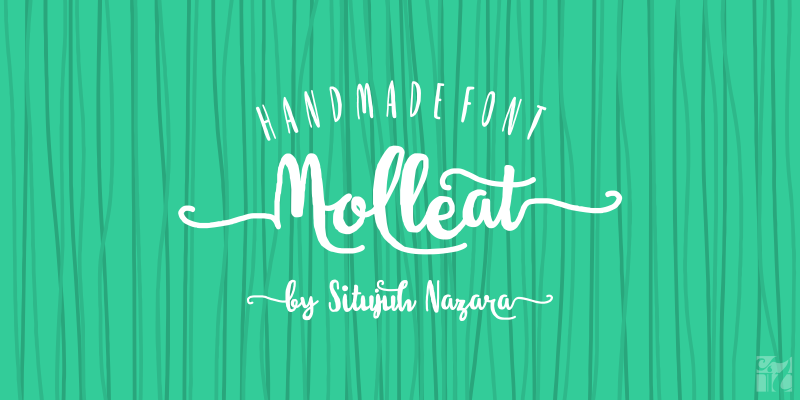
A fonte ‘Molleat Handmade Font’ é uma criação única e autêntica do designer brasileiro Situjuh Nazara. Inspirada em escrita manual, essa fonte oferece um toque autêntico à sua mensagem ou projeto. Ideal para quem busca uma impressão realista, a ‘Molleat Handmade Font’ combina sutileza com robustez, tornando-a perfeita tanto para uso pessoal quanto profissional. O design cuidadoso e detalhado permite que o texto seja legível em diversos tamanhos e formatos, garantindo uma experiência de leitura única. Além disso, a ‘Molleat Handmade Font’ pode ser usada gratuitamente com um toque humano de graça, ou você pode contribuir através de uma doação mininal de $10 USD por meio da conta PayPal de Situjuh para apoiar seu trabalho. Para aqueles que desejam licenças comerciais mais amplas, a fonte está disponível em sua plataforma oficial no Creative Fabrica. Esta é mais do que apenas uma fonte; ela é um complemento perfeito ao seu estilo e talento gráfico.